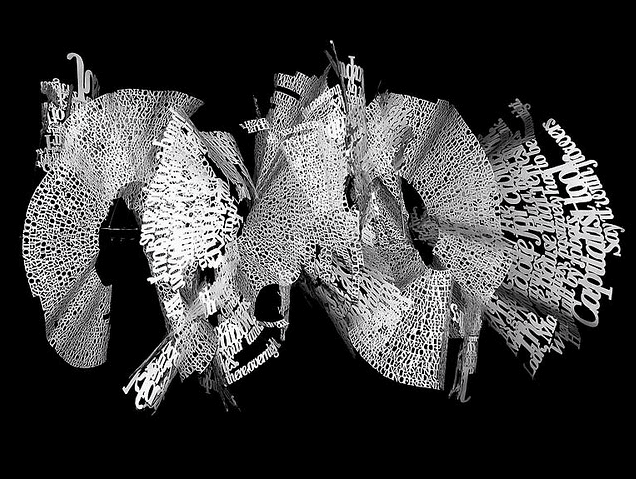
Текст является главным способом передачи информации в Сети и, как следствие, одним из важнейших компонентов веб-сайта. Естественным и логичным при таком положении дел выглядит желание любого владельца сайта добиться того, чтобы его тексты были не только информативными и увлекательными, но еще и хорошо выглядели. Для этого современные технологии веб-дизайна и верстки предоставляют обширный арсенал инструментов. Сегодня мы поговорим о самом главном из них — шрифте и особенностях его применения на веб-сайтах.
Шрифт — не просто декоративный элемент на сайте. Помимо утилитарной функции визуализации текста он играет эстетическую и психологическую роль, оказывая влияние на все аспекты взаимодействия с пользователем. Красивый шрифт, отвечающей содержанию и эстетической задаче сайта, легко и приятно читать, в то время как некачественный или не удачно подобранный шрифт превращает чтение в испытание и оставляет у посетителя неприятное впечатление. Несколько примеров использования оригинальных шрифтовых решений в дизайне веб-сайтов некоммерческих организаций:
Теперь, когда положительный эффект, производимый красивыми шрифтами на веб-сайте, стал нам очевидным, возникает резонный вопрос «так как же использовать нестандартные шрифты на сайте?». Ключ к ответу на него лежит в понимании принципа работы компьютерных шрифтов.
Компьютерный шрифт — это файл определенного формата, содержащий описание набора букв и знаков, который используется программой или операционной системой для отображения символов на экране. В этом (перефразирующем Википедию) определении содержатся несколько ключевых аспектов, которые потребуют нашего внимания при работе со шрифтами на веб-сайте.
- Файл определенного формата. Файл шрифта, чтобы его могла использовать программа, с которой мы работаем, должен быть определенного «известного этой программе» формата. Форматов компьютерных шрифтов существует несколько, что автоматически порождает проблему совместимости. Все усилия по поиску и подбору шрифта сойдут на нет, если он не поддерживается программой, в которой просматривается текст.
- Используется программой или ОС. Файл шрифта должен быть физически доступен системе, чтобы его можно было использовать для отображения текста. В условиях Интернета это — нетривиальная задача. Ведь сайт просматривается на множестве разных компьютеров, и мы вовсе не можем быть уверены, что на них есть необходимые шрифты.
- Описание набора букв и знаков. Мы должны быть уверены, что шрифт содержит глифы, описывающие все символы в отображаемом тексте. Например, если мы будем пытаться отобразить русский текст с использованием шрифта, в котором отсутствуют кириллические глифы, у нас ничего не получится.
- Применение для отображения символов. Необходимо иметь способ проинформировать программу, в которой осуществляется просмотр текста, о том, какая именно его часть должна отображаться с использованием того или иного шрифта.
Теперь, когда мы ясно видим перед собой проблемы,связанные с использованием шрифтов на веб-сайтах, давайте посмотрим как же современная веб-верстка справляется с их решением.
Поиск шрифта для веб-сайта
Самая первая задача, которую нам необходимо решить, это — найти и выбрать подходящий шрифт и убедиться, что:
- он поддерживает нужный язык (в частности, русский)
- лицензия шрифта допускает его использование на веб-сайте
- Google Webfonts — библиотека свободно-распространяемых шрифтов, созданная компанией Google, все шрифты из данной коллекции могут быть свободно использованы на любых сайтах, при этом Google также предоставляет простой интерфейс для их встраивания.
- Adobe Edge Web Fonts — аналогичный сервис от Adobe, содержащий большой каталог свободно-доступных шрифтов, средства поиска и тестирования, возможность встраивания в сайт.
- free.type.org.ua — пополняемая коллекция свободно-распространяемых шрифтов с поддержкой кириллицы.
Если в названии шрифта его кириллическая сущность не указана явно (например, Museo Sans Cyrillic), то чтобы убедиться в поддержке русского языка, необходимо либо просмотреть таблицу содержащихся в нем символов, либо попробовать что-нибудь им написать. Некоторые онлайн библиотеки предоставляют такую возможность, альтернативно можно использовать сервисы для тестирования шрифтов, например:
- Typetester — тестирование и сравнение шрифтов, путем просмотра тестового текста с настраиваемыми параметрами, такими как размер кегля, межстрочное расстояние и т.п.
- Wordmark — простой сервис тестирования шрифтов, установленных на компьютере, посредством отображения тестовой фразы, которую ввел посетитель
Шрифт можно использовать на сайте, только в случае если лицензионное соглашение (EULA) приобретенная у дизайнера или агентства разрешает это. Многие производители шрифтов (в том числе и кириллических, например, ParaType) предоставляют такую лицензию. В качестве альтернативы покупки веб-лицензии шрифта у отдельного агентства, выступают сервисы встраиваемых шрифтов (Web Font Embedding Services). Они представляют собой по сути удаленные библиотеки шрифтов, дающие своим клиентам возможность подгружать шрифты и встраивать их в свои сайты за некоторую абонентскую плату (обзор сервисов встраивания). Наиболее популярные среди них:
В завершении нашей беседы о практическом использовании веб-шрифтов на сайте — несколько подборок сайтов, отводящих веб-шрифтам ключевую роль